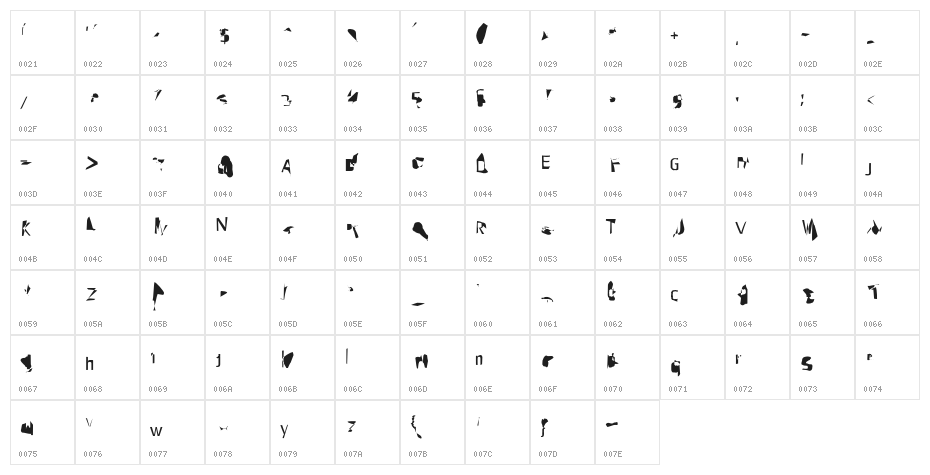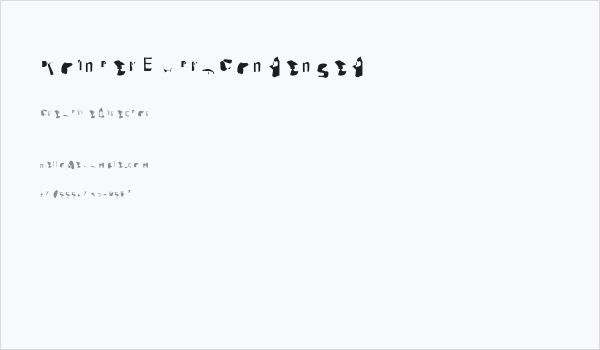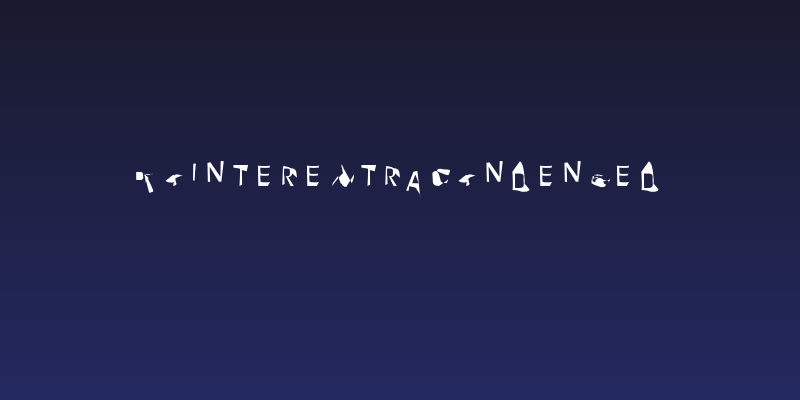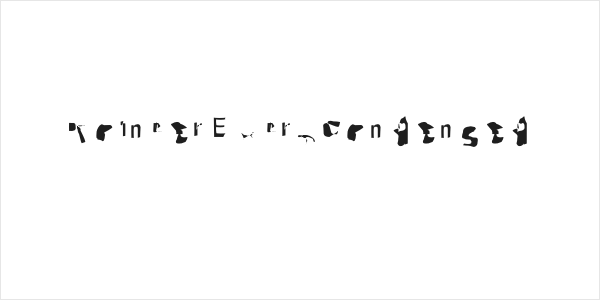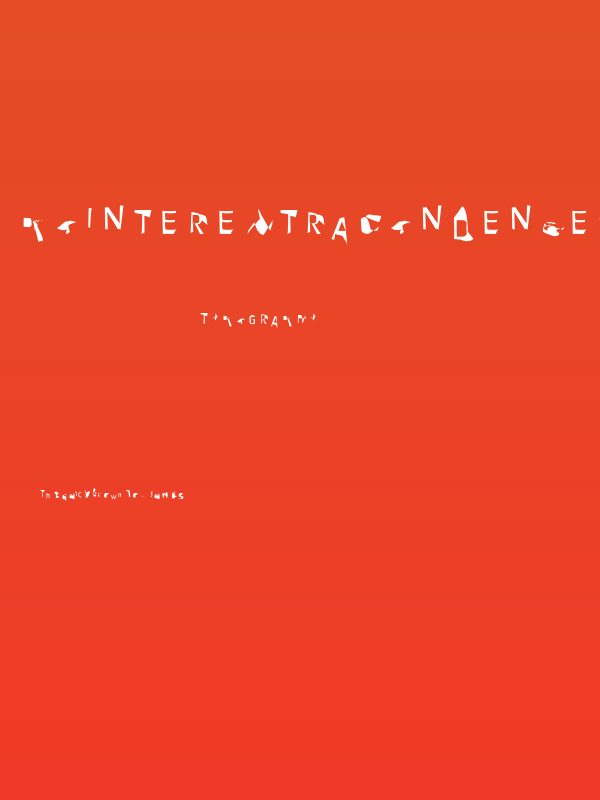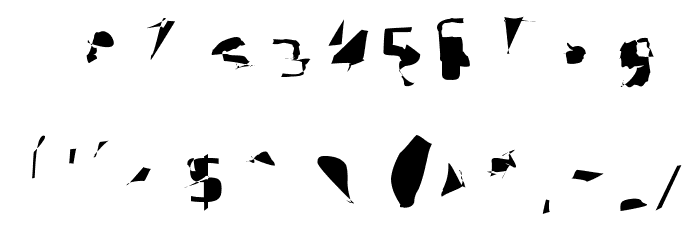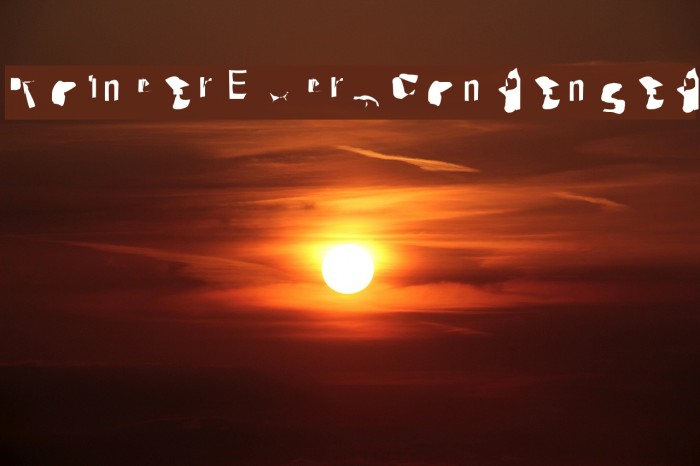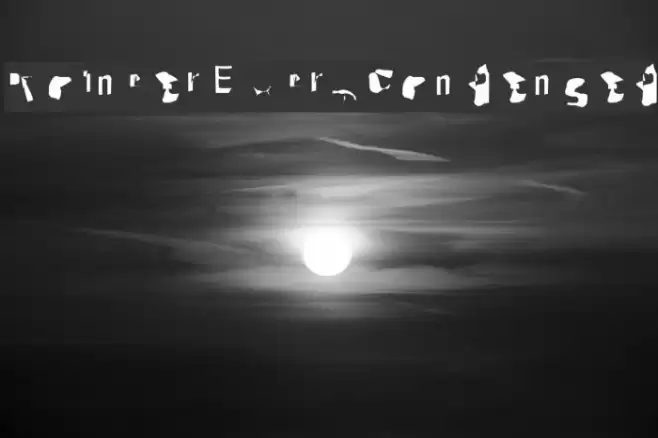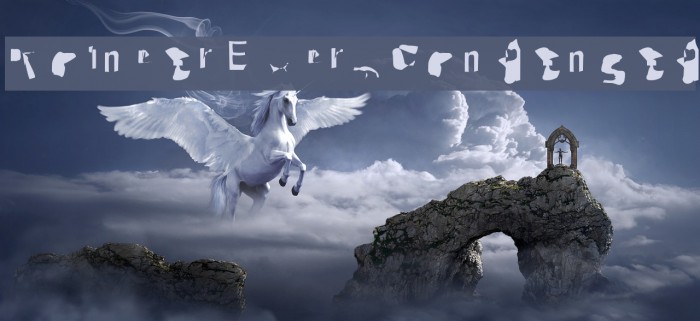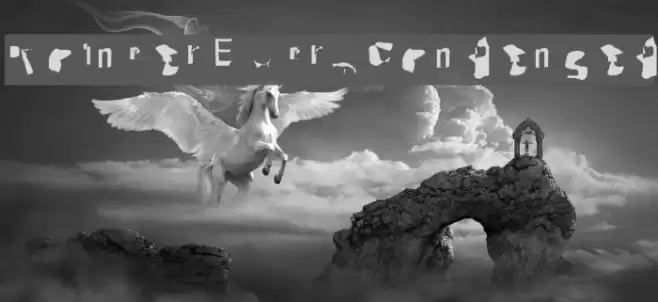
Pointer ExtraCondensed Font
✎ Distorted Eroded
| Категория | Distorted Eroded |
| Общий стиль | Modern, Abstract |
| Область применения | Logos, Posters, Artistic Designs |
| Рекомендуемые проекты | Ideal for experimental art projects, edgy graphic designs, and avant-garde posters. |